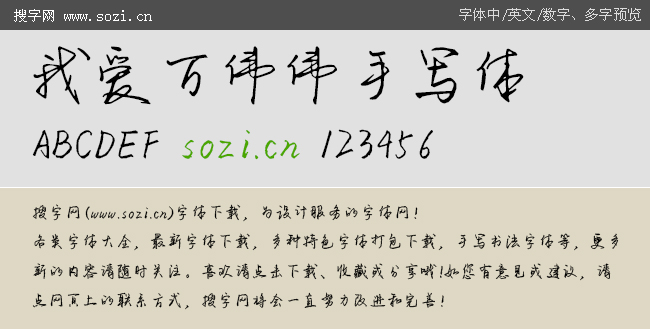
我愛萬偉偉手寫體
搜字網(wǎng)給大家提供一款我愛萬偉偉手寫體中文字體下載,我愛萬偉偉手寫體是一款浪漫的手寫字體,是作者送給女朋友的情人節(jié)禮物,一款屬她的名字的字體,每個(gè)字都存著對她的愛,字體書寫流暢,瀟灑大方,支持免費(fèi)商用。適合應(yīng)用于藝術(shù)設(shè)計(jì)、平面宣傳設(shè)計(jì)、網(wǎng)頁設(shè)計(jì)、海報(bào)設(shè)計(jì)等應(yīng)用。